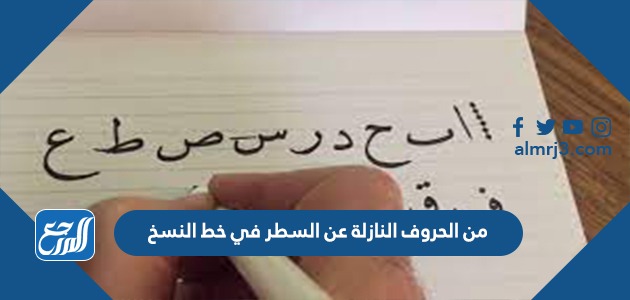
من الحروف النازلة عن السطر في خط النسخ
من الحروف النازلة عن السطر في خط النسخ، تتكون الخطوط العربية من ستة أنواعٍ رئيسية وهي خط الرّقعة، وخط النّسخ، وخط الثلث، والفارسي، والديواني، والكوفي، ويعتبر كل من خط النّسخ والرّقعة من أشهر الخطوط التي يتم استخدامها كثيراً في الكتابة فكلاهما يتشابهان بوضوح الكلمات فيهما ولكن بفروق واضحة، ومن خلالِ موقع المرجع سنتعرفُ على خط النسخ، ومُميزاتهِ، وسبب التسميّة فيه.
من الحروف النازلة عن السطر في خط النسخ
خطُ النسخِ هو أحدُ الخطوطِ العربيّة الستةّ التي تستخدمُ لأغراضِ عدّة، لما يمتازُ بهِ من البساطة والوضوح والرصانّة، وتعودُ نشأةُ هذا الخطُّ وتأسيسَهُ إلى الخطاط التُركيّ ابن مقلة شيرازي، في أواخرِ القرن التاسعِ عشر، ومن الحروفِ النازلةِ عن السطرِ في خط النسخِ:
- حروفِ الياءِ والصاد والقاف
ويستخدمُ خطُ النسخِ في كتابة الكتب التعليميّة، والمطبوعات اليوميّة، والمصاحف الكريمية، والمواقع الإلكترونيّة، وقدْ كانَ النسّاخَون يستخدمونه في نسخِ الكتب، ولهُ العديد من التسميّات أيضًا، ومنّها: البديعُ والمقوّر والمُدوّر، ويعتبرُ خطَ النسخِ هو أولُ خط يتعلّمه الناشئِة في العالم العربيّ والإسلاميّ، وقدْ سُمّي بخطِ النسخِ، بسببِ انتشار استخدامهُ بشكل كبير في نقلِ ونسخِ الكتب.[1]
مميزات خط النسخ
يمتازُ خطَ النسخِ بعدّة ميزات تميزه عن غيّره من الحروفِ العربيّة، ومنْ مميزاتِ خط النسخ:
- يمتازُ خطَ النسخ بروعةِ حروفه وجمالية تركيبه وبديع تشكيله.
- يمتازُ خطَ النسخ بأنّه من أسهل الخطوط العربيّة في القواعدِ والكتابةِ والقراءة كذلك.
- يمتازُ خطَ النسخ بوضوح وبساطة الكلمات والجمل المكتوبة فيّه، مما يجعلها سهلة القراءةِ والفهم.
- يمتازُ خطَ النسخ بتساوي أحجام الحروف فيّه.
- يمتازُ خطَ النسخ بمراعاةِ قواعدَ اللغةِ العربية التي يعتمدُ عليّها في كتابةِ الخط العربي.
- يمتازُ خطَ النسخ بالحفاظ على استخدام كتابة السنن ومراعاة تطبيق سننها.
أنواع الخطوط العربية
حاز الخط العربيّ على الاهتمامِ الفائق، وقد اعتمدت كتابةُ اللغة العربيّة على ستةِ أنواع من الخطوطِ العربيّة الأصليّة، والتي تستمدُ منّها الخطوطِ الأخرى، فالخط العربيّ هو فنٌ إسلاميْ، فهوَ نتاجَ الدين الإسلامي الحنيف، ويرتبطُ ارتباطًا وثيقًا بكتابِ الله تعالى، ومنْ أنواع الخطوط العربيّة:
- خطُ النسخ.
- الخط الكوفي.
- خط الرقعة.
- الخطُ الديواني.
- الخط الأندلسي المغربي.
- خط الإجازة.
- خط التعليق أو الخط الفارسي.
أشهر الخطاطين العرب
أحدُ أهم العوامل التي أدت إلى انتشارَ الخطَ العربي هو ارتباطهِ الوثيقُ بالدينِ الإسلامي والقرآن الكريم، وقدْ أصبح الخط العربي عملاً فنيًا ومعلمًا حضاريًا، وقد أتقنّه واشتهر به عدّة من الخطاطين العرب، ومنّهم:
- محمد بن القاسم القندوس.
- رجاء بن حيوة.
- رشدية هانم.
- سعيد النهري.
- سلمان أكبر.
- صادقين عثمان طه.
- ياقوت المستعصم.
- عبد الإله العرب.
- أسماعيل جولجو.
- أحمد حافظ.
- ابن غطوس.
- أمين الله رضائي
- بشر بن عبد الملك.
- ابن البواب.
- إبراهيم الصلحي.
- جلال أمين صالح.